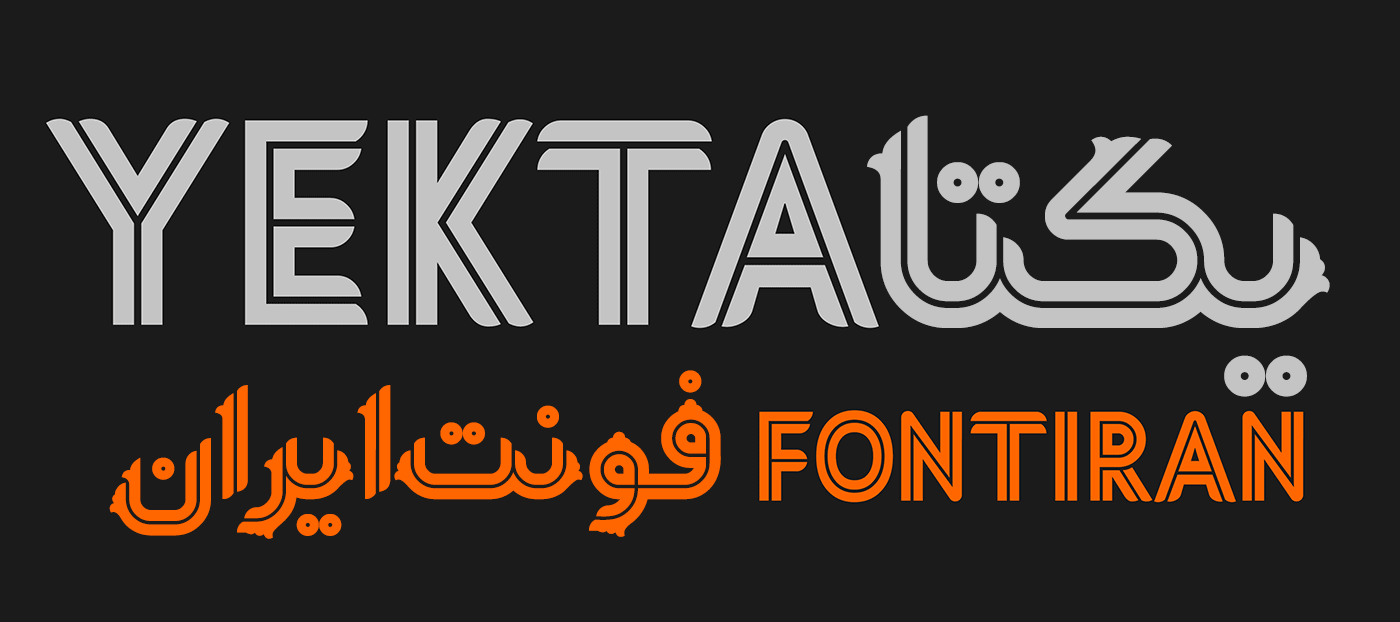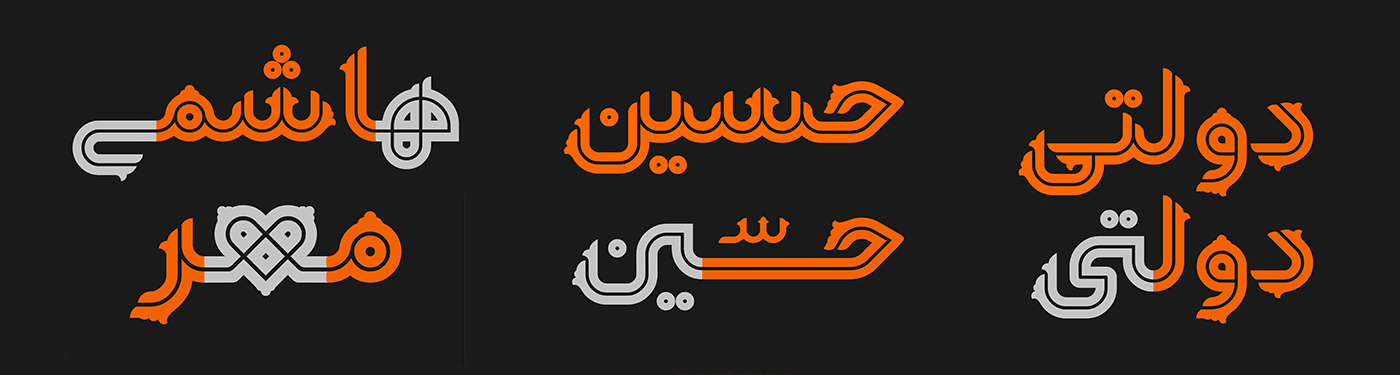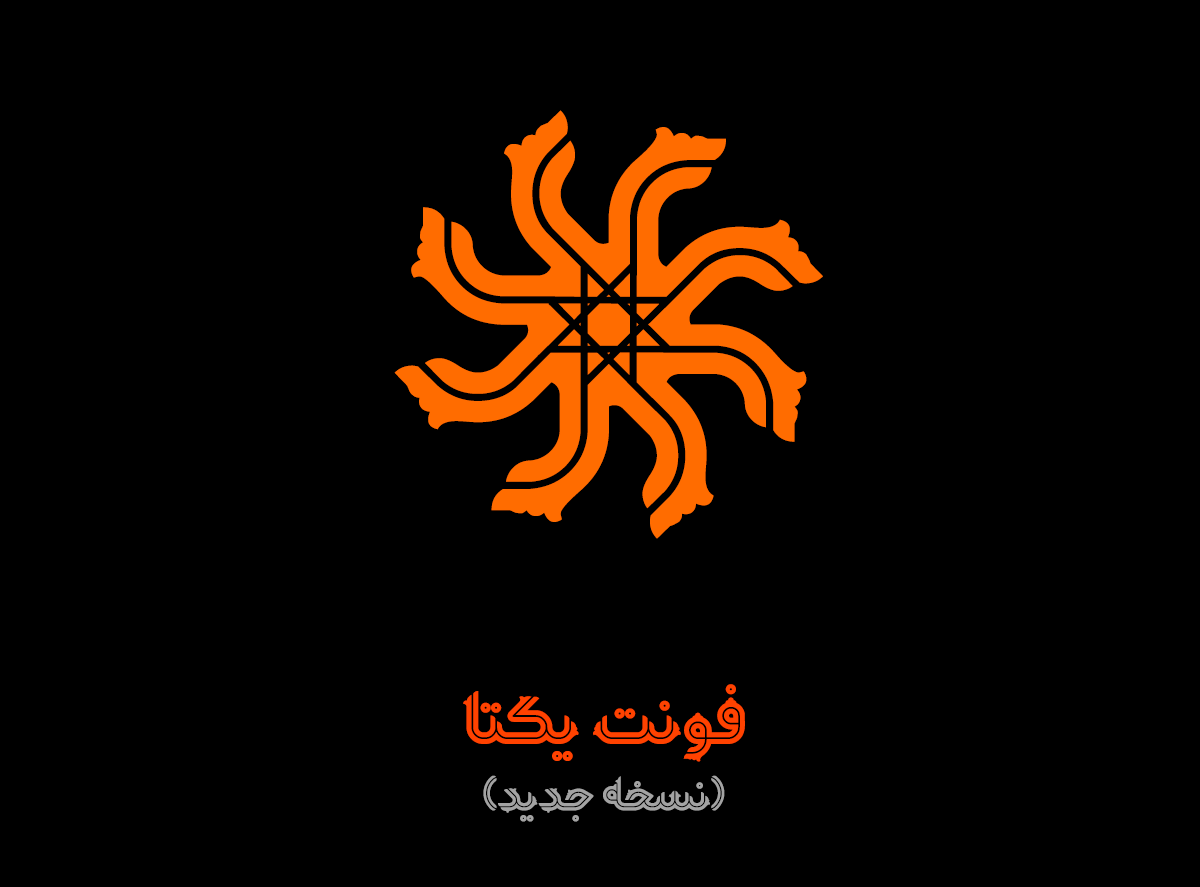
در نسخه ۲ فونت یکتا چه چیزهایی جدید است؟
۱- اضافه شدن زبان انگلیسی هماهنگ با سبک فونت.
۲- اضافه شدن ترکیبات و حروف جایگزین جدید.
۳- اضافه شدن نقشمایههای متعدد هماهنگ با سبک حروف.